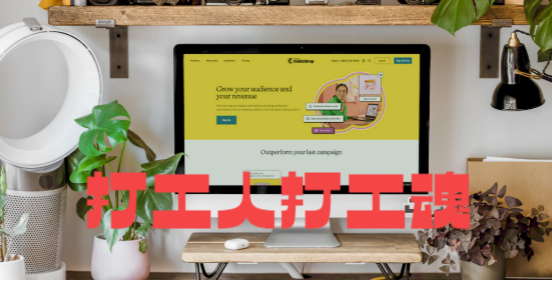
Z时代酸性设计到底是谁在喜欢啊?酸性设计风格、审美、应用一网打尽!
作为特立独行的Z时代设计师,酸性设计肯定是新潮人的首选,如果把00后作为主要主要消费人群,那么酸性设计是什么呢?应用于哪些行业呢?跟着励字战士一起来看看吧~
作为对上世纪流行文化的复刻,它复古但又不止于此,新时代的设计师们通过天马行空的构思,在保留酸性设计原汁原味的同时,注入一种面向未来的科技感。
在当代的酸性设计中,大家可以看到音乐磁带、CD 光盘、POP Art 纹样、霓虹色等大量复古的元素充斥其中。当然,也有流动扭曲的金属液态字体、3D 物件和镭射、金属、铝箔等未来元素。怀旧的视觉里,却有着了科幻未来主义的反乌托邦场景,跟大家推荐两款酸性复古字体,让复古与未来在这里兼容碰撞,撞出新的火花。
励字逆反差圆舞简,字型方正、软硬兼备、笔画粗细对比明显的逆反差圆弧字体。在逆反差直线版基础上将撇笔画、捺笔画、钩笔画、部分点笔画运用弧线处理、弧度饱满。中宫较大,重心平稳。笔画对称。
励字逆反差踢踏简,字型规整方正,笔画的粗细对比明显。是一款横平竖直、顶部底部笔画厚重、中间笔画极细的逆反差直线字体。起笔收笔采用平直的特点,中宫宽阔、重心平稳、布白均匀。笔画摒弃繁琐特点,转折处均以直角的处理方式。顶部底部笔画灰度极度夸张。点笔画根据空间有多种表达方式、灵活多变。笔画对称、镜像的处理方式使得结构更为工整。